Những thiết kế mang tinh thần Á Đông luôn có sức hút riêng nhờ sự hòa quyện giữa nét cổ kính, thư pháp mềm mại và bản sắc truyền thống đậm đà. Từ cảm hứng cổ trang Trung Hoa, tinh thần võ hiệp Nhật Bản cho đến thư pháp Phật giáo hay dịp lễ hội truyền thống – các font chữ Việt hóa phong cách Á Đông dưới đây sẽ giúp bạn truyền tải trọn vẹn tinh thần ấy vào từng thiết kế.
Danh sách này được tổng hợp từ bộ sưu tập chính thức trên FontVN, với nhiều font miễn phí lẫn cao cấp, phù hợp dùng cho poster phim, bao bì sản phẩm, banner Tết, truyện tranh kiếm hiệp, sự kiện văn hóa, hay thiết kế branding mang đậm chất châu Á.
Font chữ mang đậm hơi thở võ sĩ đạo Nhật Bản, với các đường nét mạnh mẽ, chắc chắn nhưng vẫn giữ được sự cổ điển trong từng ký tự. Phù hợp với những thiết kế cần sự oai phong, thần thái dứt khoát và cá tính.
Mang phong cách Brush hiện đại, font thư pháp này vừa truyền thống vừa tươi mới, tạo cảm giác nghệ thuật và sống động. Nét vẽ uyển chuyển giúp truyền tải cảm xúc và tinh thần tự do trong từng chữ viết.
Một sự pha trộn giữa cổ điển và hiện đại, mang đến phong cách quý tộc trang trọng. Font có cấu trúc mạnh, chi tiết tinh xảo, thích hợp cho các thiết kế cao cấp mang hơi hướng Á – Âu hoài cổ.
Gợi nhớ đến các bảng hiệu cổ xưa hay tiêu đề phim Trung Hoa kinh điển, font này sở hữu nét chữ đậm, cân đối và sang trọng. Dễ dùng trong các thiết kế truyền thống hoặc hiện đại hóa nét văn hóa xưa.
Font chữ đáng yêu, gần gũi được thiết kế cho các dịp lễ như Trung Thu, Tết cổ truyền. Kết hợp giữa nét trẻ trung và không khí lễ hội, đây là lựa chọn lý tưởng cho các ấn phẩm mùa Tết dành cho thiếu nhi hoặc gia đình.
Nổi bật với hình ảnh con rồng – biểu tượng quyền lực phương Đông – font này thể hiện sự mạnh mẽ, uốn lượn và linh hoạt. Nét chữ khỏe, tạo ấn tượng ngay từ cái nhìn đầu tiên, rất hợp với chủ đề văn hóa cổ truyền, võ hiệp.
Đậm chất thư pháp cổ điển nhưng vẫn giữ được sự gọn gàng, dễ đọc. Đây là một trong những font thư pháp hiếm hoi có tính ứng dụng cao, vừa thích hợp làm tiêu đề, vừa có thể dùng cho các đoạn text ngắn mang chất thơ.
Phong cách game kiếm hiệp, thể thao và giả tưởng kết hợp trong một font chữ đầy năng lượng. Dễ bắt gặp trong các banner sự kiện, tiêu đề truyện tranh hành động hay các dự án mang màu sắc thần thoại.
Là sự tái hiện phong cách “hiệp khách giang hồ” với các nét vẩy mực phóng khoáng. Font như được viết bằng cọ thư pháp đầy khí chất, tạo cảm giác cổ trang, phiêu lưu và hào sảng.
Mềm mại, thanh thoát như những nét vẽ trong tranh thủy mặc, font này thích hợp với các thiết kế mang tính thiền định, thơ mộng hoặc cần không khí Á Đông nhẹ nhàng, sâu lắng.
Lấy cảm hứng từ văn hóa Ấn Độ và Phật giáo, font chữ này mang vẻ đẹp huyền bí, thanh cao và tinh tế. Thích hợp trong các thiết kế thiền, tôn giáo hoặc dịp lễ tâm linh truyền thống.
Một font độc đáo với phong cách mây khói, mềm mại và thanh lịch. Dù mang vẻ nhẹ nhàng nhưng font vẫn giữ được độ nhận diện cao, đặc biệt hiệu quả trong thiết kế chủ đề Tết và lễ hội cổ truyền.
Font Brush thư pháp đẹp mắt với những nét vẽ giàu cảm xúc, như được viết tay trên giấy gió. Tạo nên không khí hoài cổ, thích hợp cho thơ, câu đối hoặc thiết kế mang chất “trữ tình dân tộc”.
Font nhẹ nhàng, tươi mới như một làn gió xuân. Tuy không quá cổ điển, nhưng vẫn giữ được tinh thần Á Đông khi dùng trong các thiết kế dịp Tết hay chủ đề tình cảm nhẹ nhàng, truyền thống.
Font bút lông đậm, mạnh mẽ và phóng khoáng – lý tưởng để tạo tiêu đề hoặc chữ ký mang hơi thở thư pháp hiện đại. Các nét chữ như bút lông in lên lụa, rất nghệ thuật nhưng vẫn dễ đọc.
Font chữ Arena mang đến vẻ đẹp tinh tế, pha trộn giữa phong cách cổ điển và hiện đại. Với các nét đậm, chắc chắn, font chữ này thể hiện sự mạnh mẽ nhưng vẫn giữ được sự mềm mại và thanh thoát nhờ các đường cong mượt mà.
Những font chữ phong cách Á Đông không chỉ giúp tăng tính thẩm mỹ mà còn truyền tải trọn vẹn không khí văn hóa, tinh thần cổ truyền đến người xem. Hãy lưu lại bộ sưu tập này để sử dụng trong các dịp lễ Tết, thiết kế bao bì truyền thống, hay bất kỳ dự án nào cần đậm chất phương Đông.
Danh sách này được tổng hợp từ bộ sưu tập chính thức trên FontVN, với nhiều font miễn phí lẫn cao cấp, phù hợp dùng cho poster phim, bao bì sản phẩm, banner Tết, truyện tranh kiếm hiệp, sự kiện văn hóa, hay thiết kế branding mang đậm chất châu Á.
1. DVN Shojumaru Việt hóa
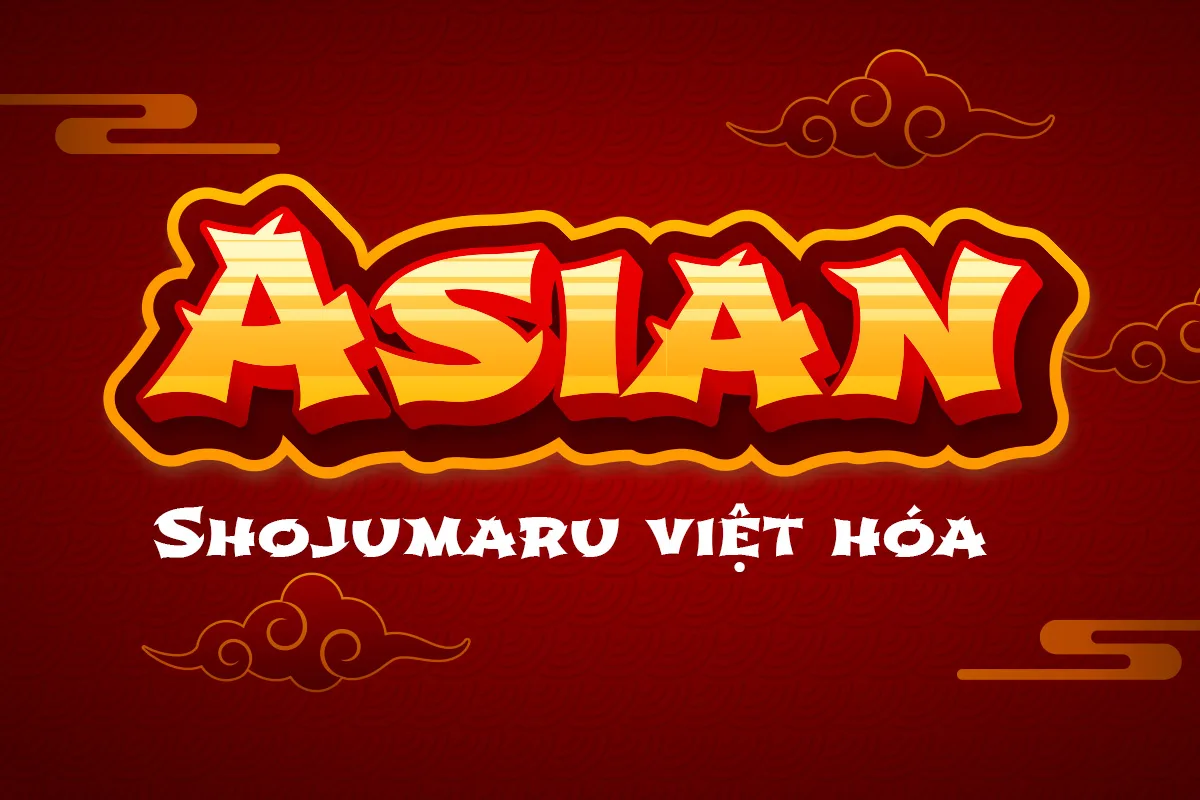
Font chữ mang đậm hơi thở võ sĩ đạo Nhật Bản, với các đường nét mạnh mẽ, chắc chắn nhưng vẫn giữ được sự cổ điển trong từng ký tự. Phù hợp với những thiết kế cần sự oai phong, thần thái dứt khoát và cá tính.
2. Thư Pháp Lạc Hồng Việt hóa
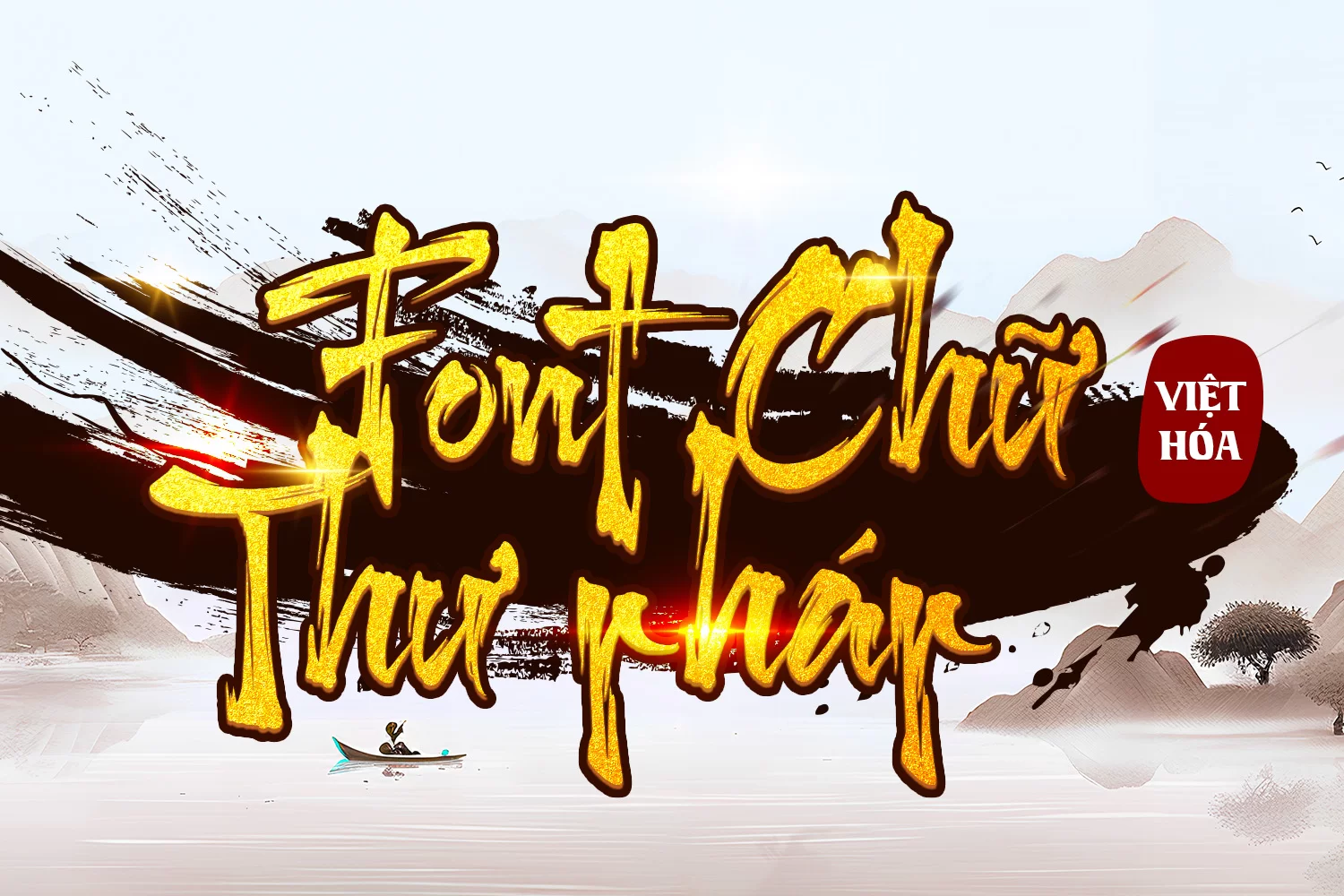
Mang phong cách Brush hiện đại, font thư pháp này vừa truyền thống vừa tươi mới, tạo cảm giác nghệ thuật và sống động. Nét vẽ uyển chuyển giúp truyền tải cảm xúc và tinh thần tự do trong từng chữ viết.
3. DVN Reloading Việt hóa
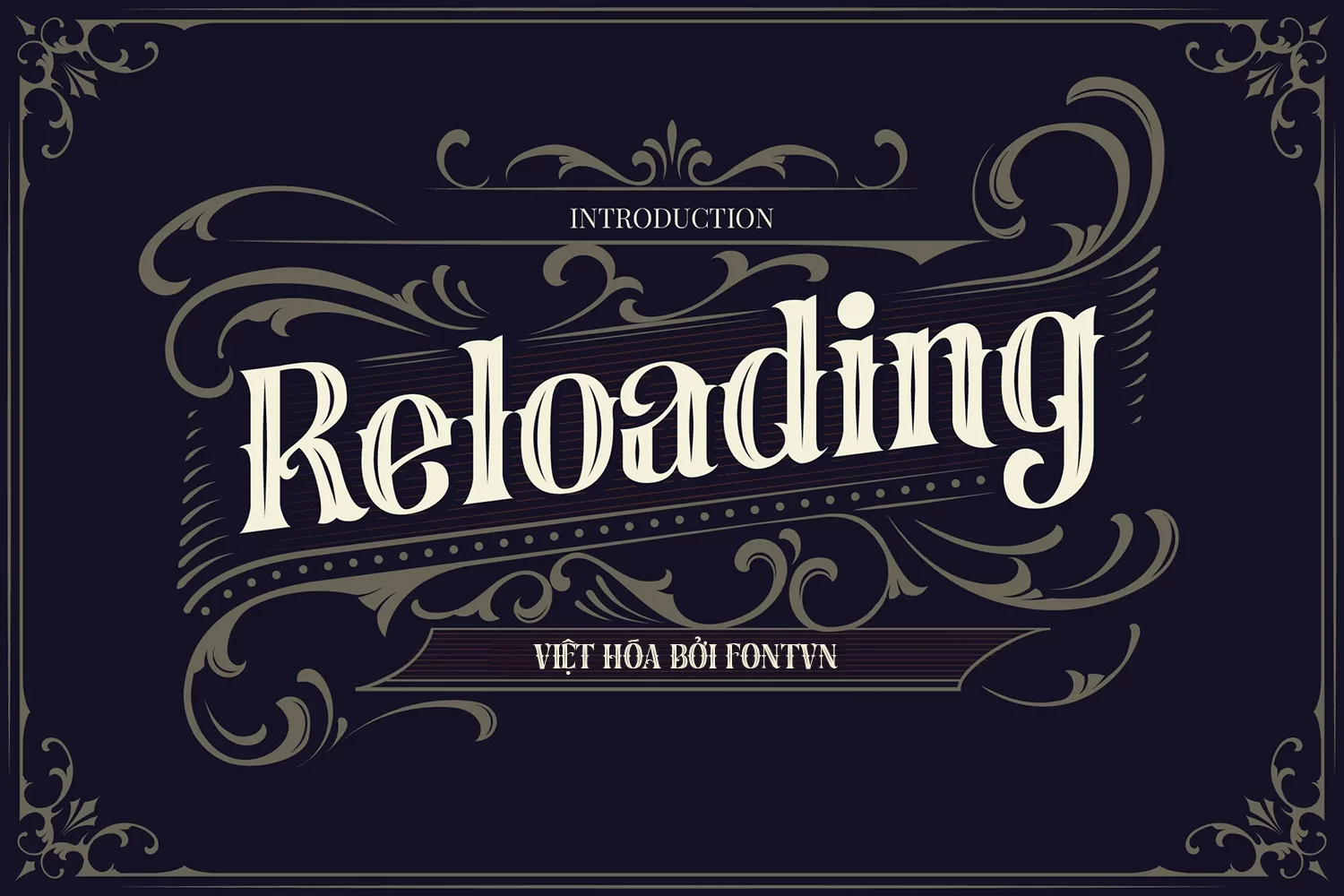
Một sự pha trộn giữa cổ điển và hiện đại, mang đến phong cách quý tộc trang trọng. Font có cấu trúc mạnh, chi tiết tinh xảo, thích hợp cho các thiết kế cao cấp mang hơi hướng Á – Âu hoài cổ.
4. DVN Kim Bảo Việt hóa
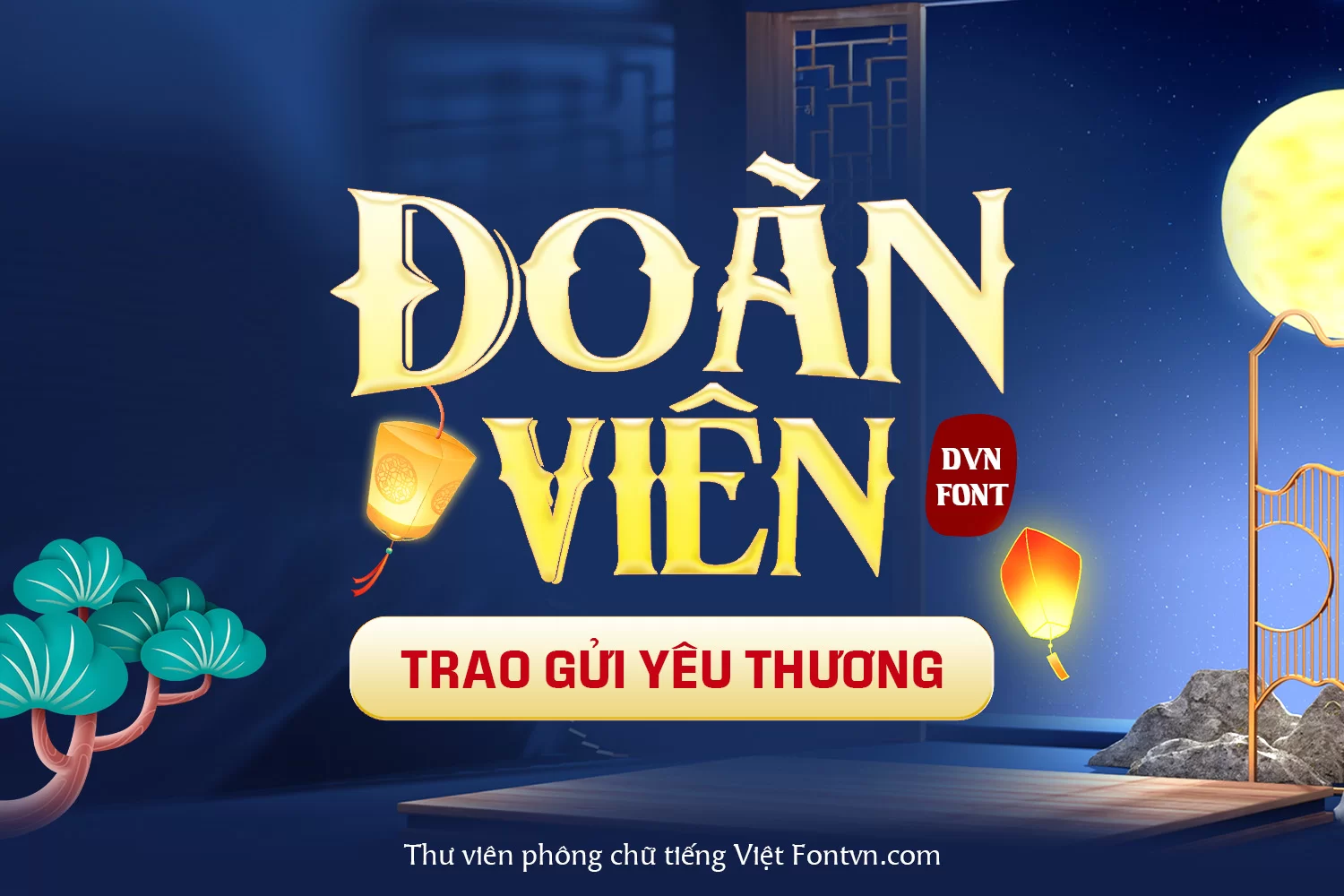
Gợi nhớ đến các bảng hiệu cổ xưa hay tiêu đề phim Trung Hoa kinh điển, font này sở hữu nét chữ đậm, cân đối và sang trọng. Dễ dùng trong các thiết kế truyền thống hoặc hiện đại hóa nét văn hóa xưa.
5. KZ Bladerunner Việt hóa (Free)
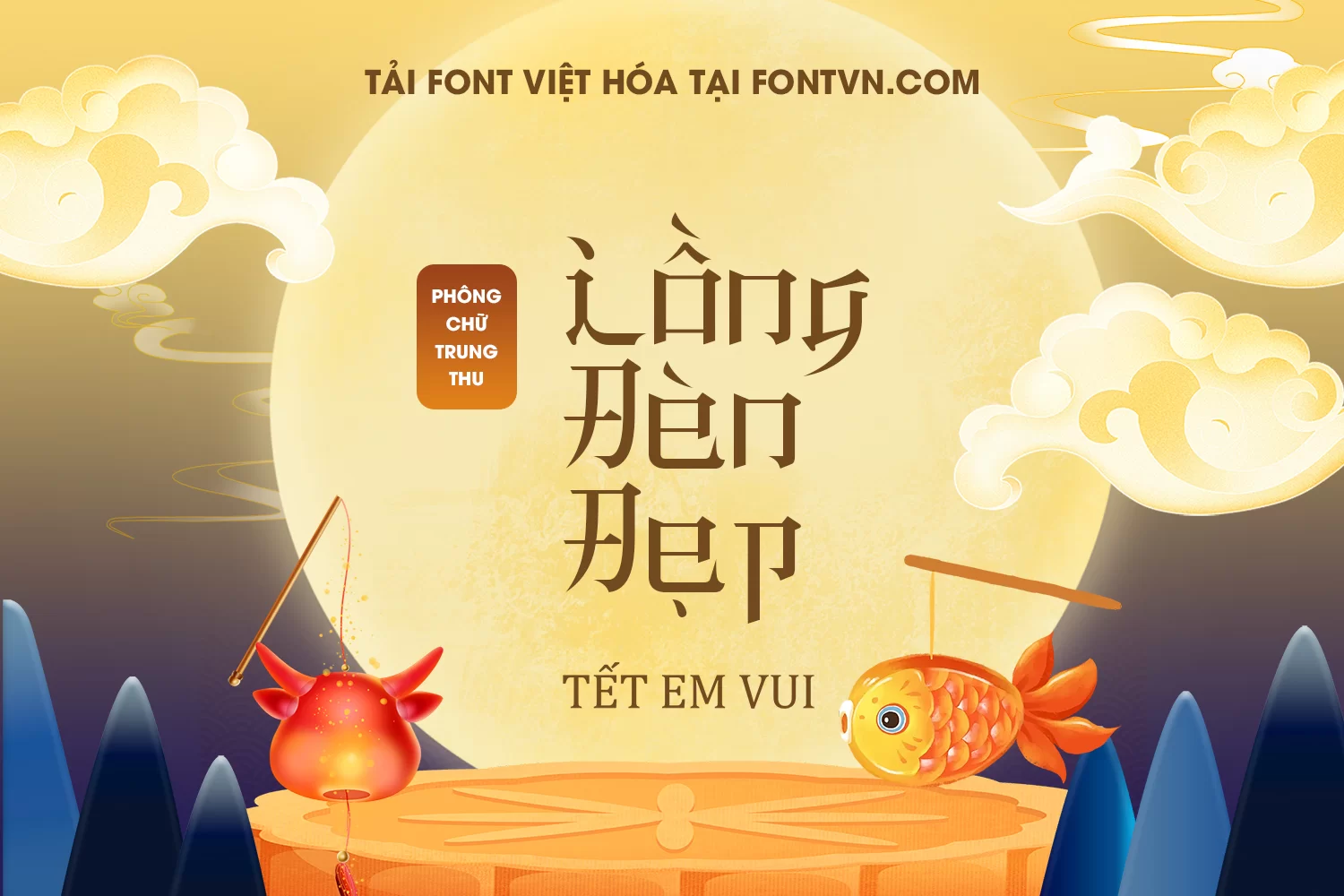
Font chữ đáng yêu, gần gũi được thiết kế cho các dịp lễ như Trung Thu, Tết cổ truyền. Kết hợp giữa nét trẻ trung và không khí lễ hội, đây là lựa chọn lý tưởng cho các ấn phẩm mùa Tết dành cho thiếu nhi hoặc gia đình.
6. DVN Dragon Việt hóa
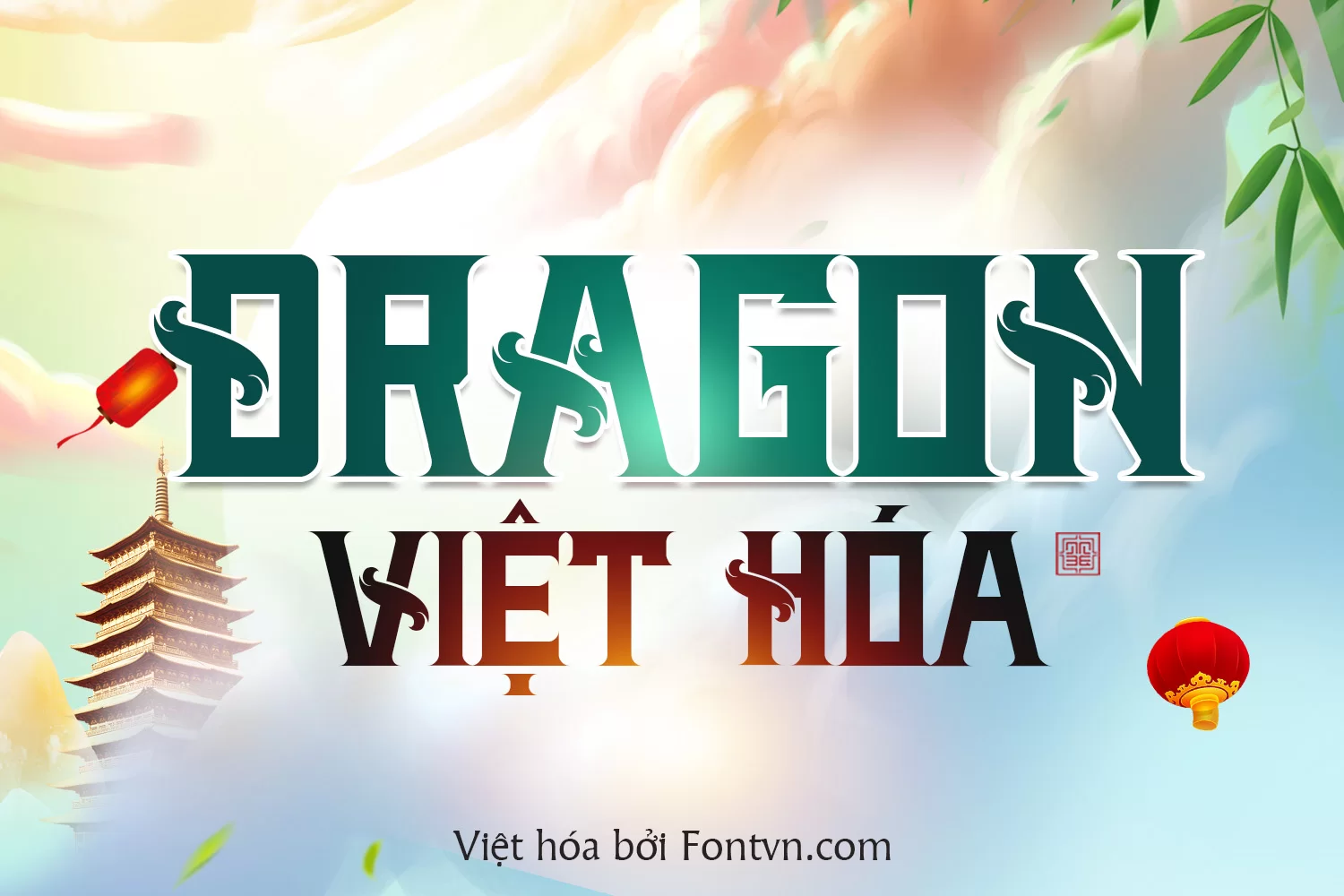
Nổi bật với hình ảnh con rồng – biểu tượng quyền lực phương Đông – font này thể hiện sự mạnh mẽ, uốn lượn và linh hoạt. Nét chữ khỏe, tạo ấn tượng ngay từ cái nhìn đầu tiên, rất hợp với chủ đề văn hóa cổ truyền, võ hiệp.
7. DVN Vô Kiếm Việt hóa
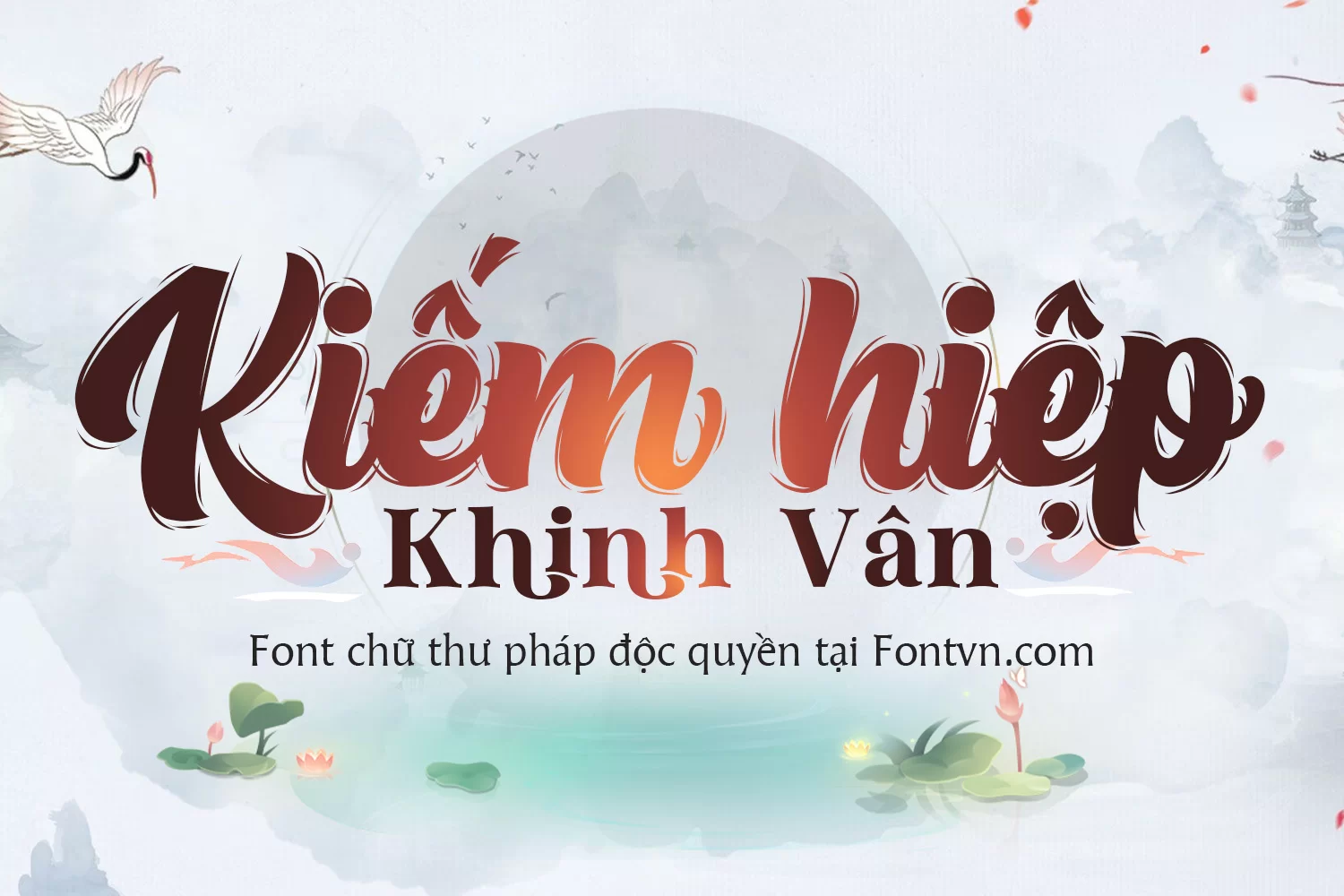
Đậm chất thư pháp cổ điển nhưng vẫn giữ được sự gọn gàng, dễ đọc. Đây là một trong những font thư pháp hiếm hoi có tính ứng dụng cao, vừa thích hợp làm tiêu đề, vừa có thể dùng cho các đoạn text ngắn mang chất thơ.
8. DVN Thiên Long Việt hóa
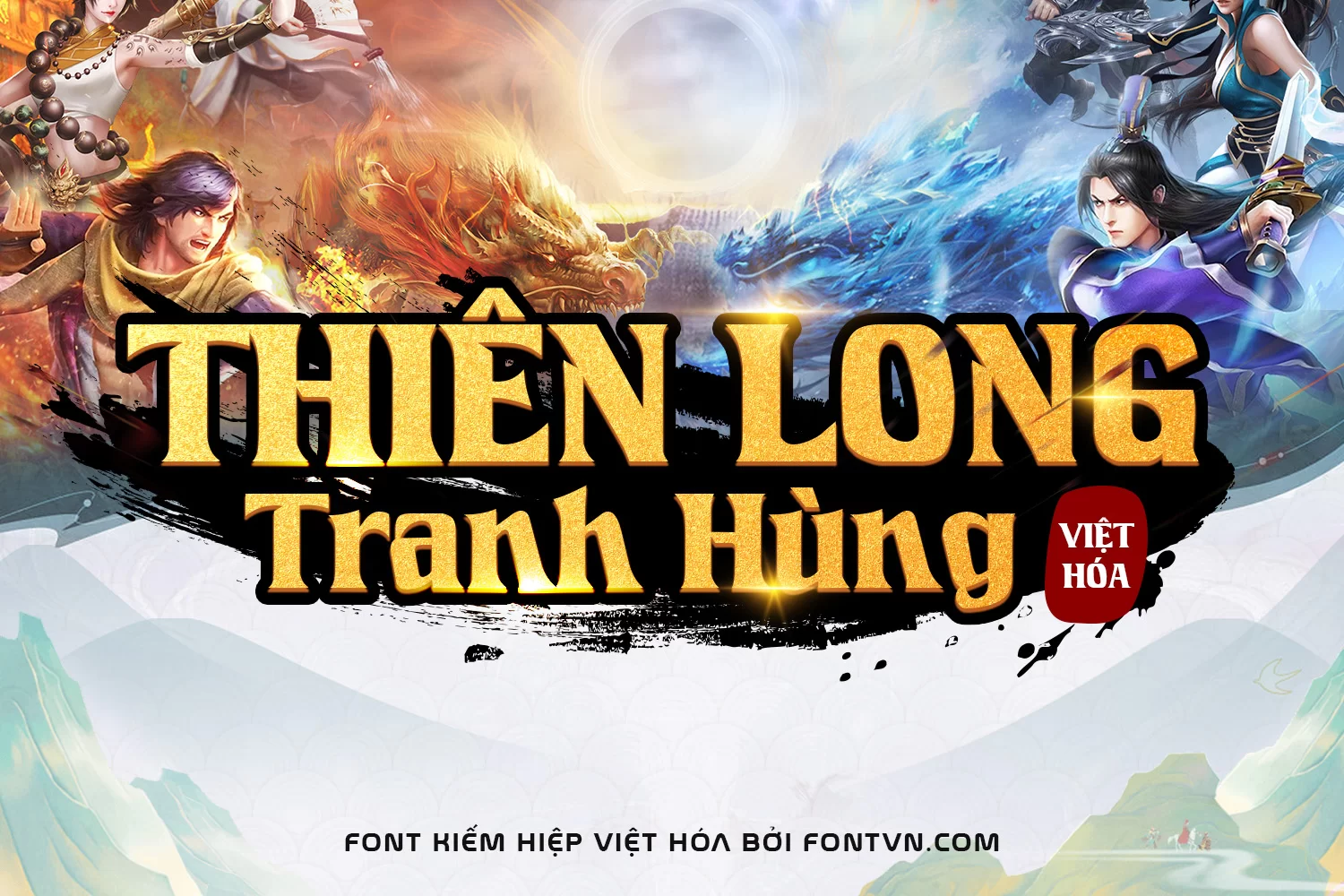
Phong cách game kiếm hiệp, thể thao và giả tưởng kết hợp trong một font chữ đầy năng lượng. Dễ bắt gặp trong các banner sự kiện, tiêu đề truyện tranh hành động hay các dự án mang màu sắc thần thoại.
9. DVN Knight Việt hóa
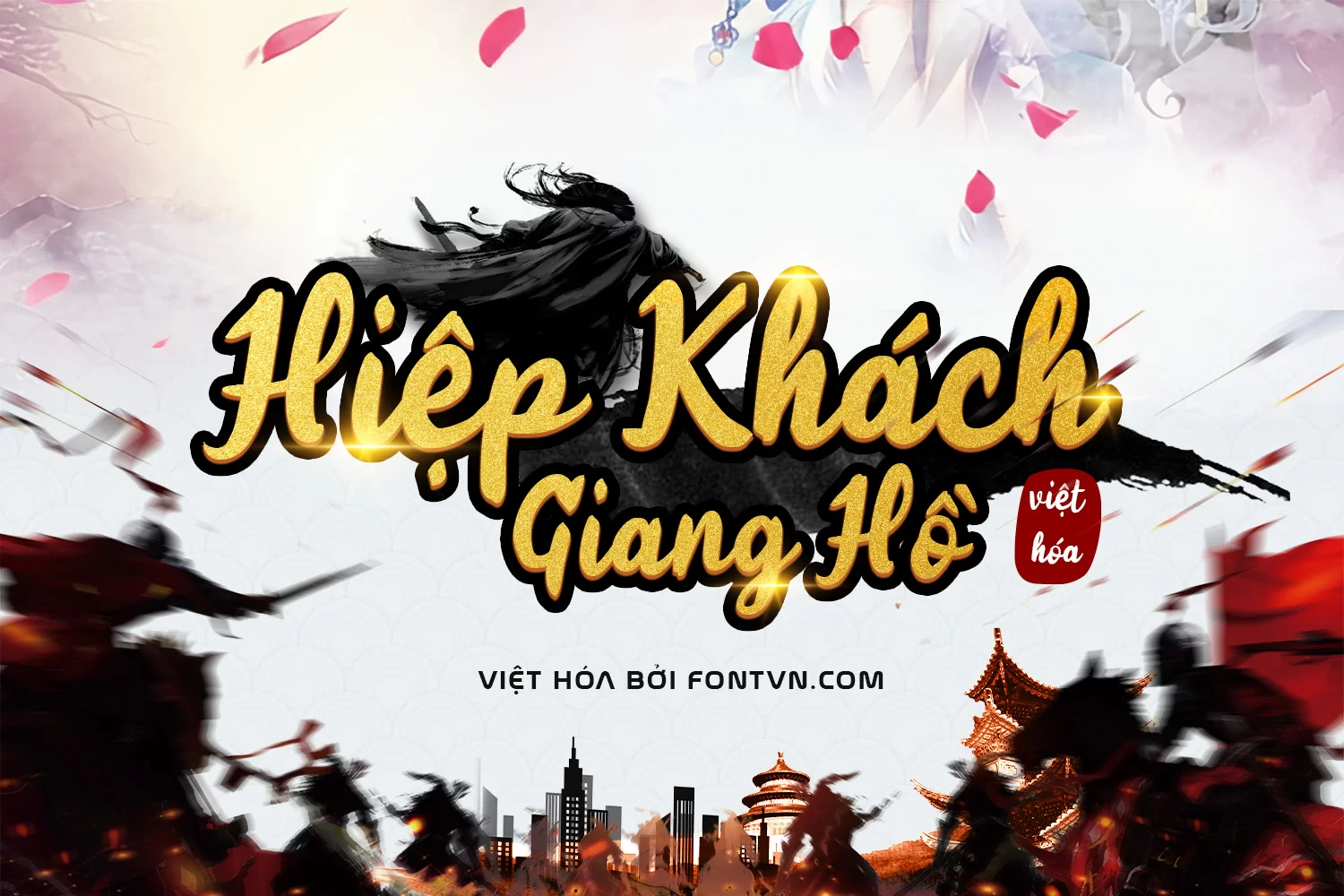
Là sự tái hiện phong cách “hiệp khách giang hồ” với các nét vẩy mực phóng khoáng. Font như được viết bằng cọ thư pháp đầy khí chất, tạo cảm giác cổ trang, phiêu lưu và hào sảng.
10. LNTH Water Dragon Việt hóa (Free)
Mềm mại, thanh thoát như những nét vẽ trong tranh thủy mặc, font này thích hợp với các thiết kế mang tính thiền định, thơ mộng hoặc cần không khí Á Đông nhẹ nhàng, sâu lắng.
11. KD Hidayatullah Việt hóa (Free)
Lấy cảm hứng từ văn hóa Ấn Độ và Phật giáo, font chữ này mang vẻ đẹp huyền bí, thanh cao và tinh tế. Thích hợp trong các thiết kế thiền, tôn giáo hoặc dịp lễ tâm linh truyền thống.
12. ShiTianSong Việt hóa (Free)
Một font độc đáo với phong cách mây khói, mềm mại và thanh lịch. Dù mang vẻ nhẹ nhàng nhưng font vẫn giữ được độ nhận diện cao, đặc biệt hiệu quả trong thiết kế chủ đề Tết và lễ hội cổ truyền.
13. LNTH – DeBorstel Brush Việt hóa
Font Brush thư pháp đẹp mắt với những nét vẽ giàu cảm xúc, như được viết tay trên giấy gió. Tạo nên không khí hoài cổ, thích hợp cho thơ, câu đối hoặc thiết kế mang chất “trữ tình dân tộc”.
14. LNTH – Manis Banget Việt hóa (Free)
Font nhẹ nhàng, tươi mới như một làn gió xuân. Tuy không quá cổ điển, nhưng vẫn giữ được tinh thần Á Đông khi dùng trong các thiết kế dịp Tết hay chủ đề tình cảm nhẹ nhàng, truyền thống.
15. DVN BrushSaga Việt hóa
Font bút lông đậm, mạnh mẽ và phóng khoáng – lý tưởng để tạo tiêu đề hoặc chữ ký mang hơi thở thư pháp hiện đại. Các nét chữ như bút lông in lên lụa, rất nghệ thuật nhưng vẫn dễ đọc.
16. DVN ARENA Việt hóa
Font chữ Arena mang đến vẻ đẹp tinh tế, pha trộn giữa phong cách cổ điển và hiện đại. Với các nét đậm, chắc chắn, font chữ này thể hiện sự mạnh mẽ nhưng vẫn giữ được sự mềm mại và thanh thoát nhờ các đường cong mượt mà.
Những font chữ phong cách Á Đông không chỉ giúp tăng tính thẩm mỹ mà còn truyền tải trọn vẹn không khí văn hóa, tinh thần cổ truyền đến người xem. Hãy lưu lại bộ sưu tập này để sử dụng trong các dịp lễ Tết, thiết kế bao bì truyền thống, hay bất kỳ dự án nào cần đậm chất phương Đông.